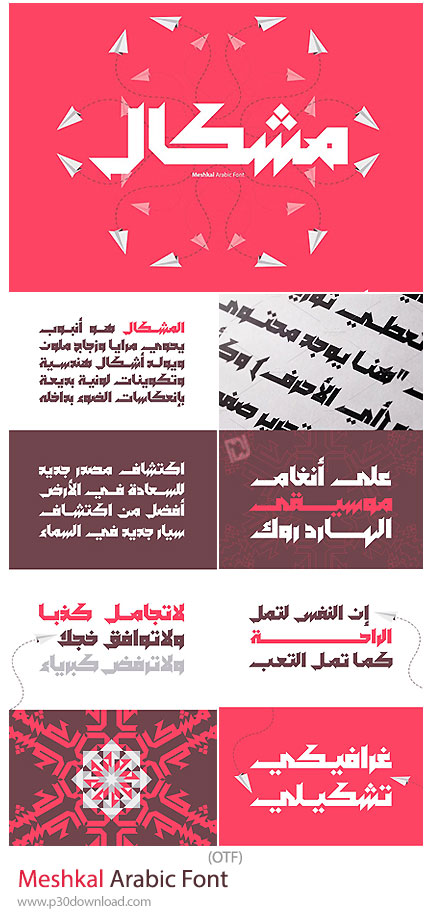
در این بخش شاهد فونت عربی مشکال می باشید که با فرمت OTF بر روی سایت برای دانلود قرار گرفته است. Meshkal یک فونت نمایشی (Display Font) عربی با طراحی منحصربهفرد و مدرن است که از الگوها و ساختارهای هندسی کالیدوسکوپی (Kaleidoscopic Geometries) الهام گرفته شده است. نام این فونت از واژه عربی «مشکال» به معنای کالیدوسکوپ گرفته شده و بهخوبی بازتابدهنده سبک هندسی و چشمنواز آن است. این فونت با ساختاری مستحکم، خطوط ضخیم و لبههای تیز طراحی شده و برای پروژههایی که نیاز به تایپوگرافی شاخص، مدرن و متفاوت دارند، گزینهای ایدهآل محسوب میشود. طراحی خاص Meshkal باعث میشود در عناوین، پوسترها، برندینگ و پروژههای گرافیکی جلوهای قدرتمند و متمایز ایجاد کند. اگر به دنبال یک فونت عربی با هویت هندسی، مدرن و متفاوت هستید، Meshkal Arabic Font با الهام از ساختارهای کالیدوسکوپی و طراحی قدرتمند خود میتواند انتخابی عالی برای پروژههای تایپوگرافی، پوستر، برندینگ و طراحیهای خلاقانه باشد.
کاربردها:
- طراحی پوستر و بنر تبلیغاتی
- طراحی لوگوتایپ و برندینگ
- جلد کتاب و مجلات
- طراحی شبکههای اجتماعی
- پروژههای فرهنگی و هنری
- طراحی رابط کاربری و وبسایت
- تایپوگرافی مدرن عربی و فارسی